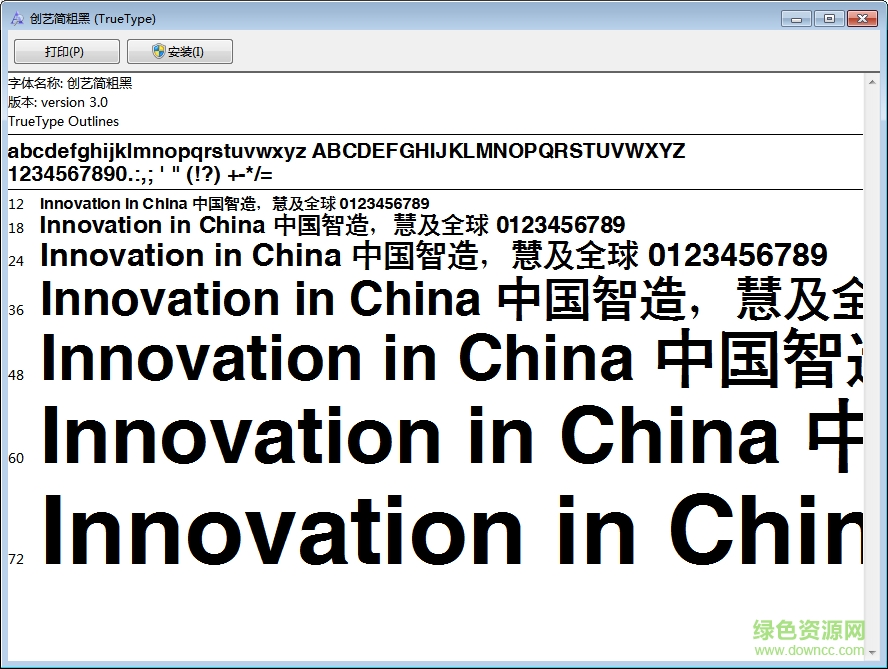
創(chuàng)藝簡粗黑體是一款非常好用的創(chuàng)藝粗體字體,支持中英文和阿拉伯?dāng)?shù)字的輸入,字體非常的平整順滑,由于自帶粗體效果,非常適合用于廣告印刷行業(yè),歡迎大家到綠色資源網(wǎng)下載使用!
本款字體端正,大氣、壁畫橫平豎直,筆跡全部一樣粗細(xì),整體效果十分不錯(cuò),可適用于廣告設(shè)計(jì)、平面設(shè)計(jì)、印刷包裝、報(bào)紙雜志等行業(yè)